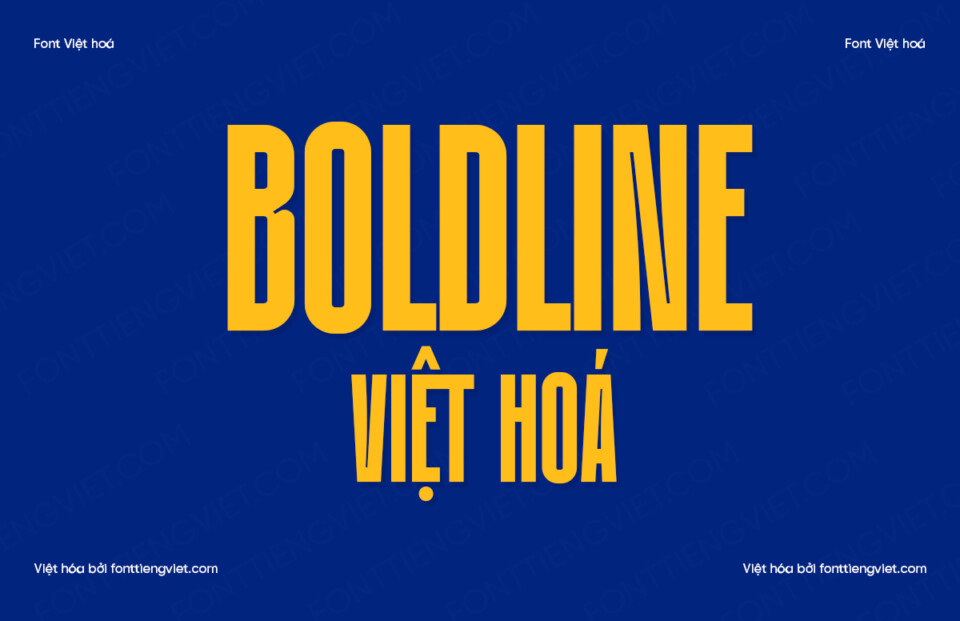
Font Việt hóa 1FTV VIP Boldline
Tải Ngay Font Việt Hóa 1FTV VIP Boldline Miễn Phí Cho Thiết Kế Thầy Cô Và Học SinhGiới thiệu bộ Font Việt hóa 1FTV VIP Boldline ấn tượngTrong môi trường giáo dục hiện đại, việc truyền tải kiến thức một cách trực quan luôn được ưu tiên hàng đầu. Bộ Font Việt hóa 1FTV VIP Boldline xuất hiện như một giải pháp hoàn hảo giúp các bài giảng, báo cáo và tài liệu học tập trở nên sinh động hơn. Đây là kiểu chữ sở hữu đường nét dày dặn, mạnh mẽ và vô cùng hiện đại. Đối với thầy cô giáo và các em học sinh, việc sở hữu một Font Miễn Phí chất lượng như thế này sẽ giúp tối ưu hóa thời gian thiết kế slide bài giảng Powerpoint. Kiểu chữ này đã được tinh chỉnh font chữ tiếng Việt hoàn chỉnh, không lo lỗi font khi gõ dấu.Ứng dụng thực tế của font chữ trong nhà trườngThiết kế bài giảng trực quanĐường nét đậm nét của bộ chữ giúp học sinh dễ dàng theo dõi bài học từ xa, kích thích tinh thần học tập sáng tạo và tiếp thu kiến thức nhanh chóng.Làm báo tường và chứng nhậnKiểu chữ này rất phù hợp để làm tiêu đề cho các tờ báo tường, poster sự kiện trường học hoặc các mẫu giấy khen, bằng khen học sinh giỏi cuối năm.Hướng dẫn cài đặt nhanh chóng và an toànĐể sử dụng, người dùng chỉ cần tải tệp định dạng .ttf hoặc .otf về máy tính cá nhân. Sau đó, nhấp đúp chuột vào tệp tin và nhấn nút Install là hệ thống sẽ tự động cập nhật vào các phần mềm như Word, PowerPoint hay Photoshop.Kết luận về bộ phông chữ đặc biệt nàyCó thể khẳng định rằng, phông chữ này là công cụ hỗ trợ đắc lực cho việc dạy và học. Hãy truy cập ngay Font Miễn Phí, Font Việt Hóa, Font Việt hóa 1FTV VIP Boldline để tải xuống công cụ tuyệt vời này, giúp nâng cao chất lượng thẩm mỹ cho mọi sản phẩm giáo dục của bạn.